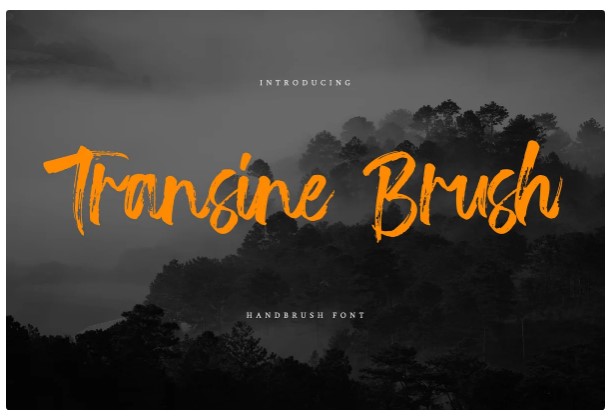
Creativemarket Transine Brush Font
[Creativemarket] Transine Brush Font
Кистевой шрифт Transine, современный подход к дизайну, ручной натуральный с неровной базовой линией. Подходит для использования в дизайне заголовков. Например, одежда, приглашения, титлы книг, дизайн канцелярских принадлежностей, цитаты, брендинг, логотипы, поздравительные открытки, футболки, дизайн упаковки, плакаты и многое другое.